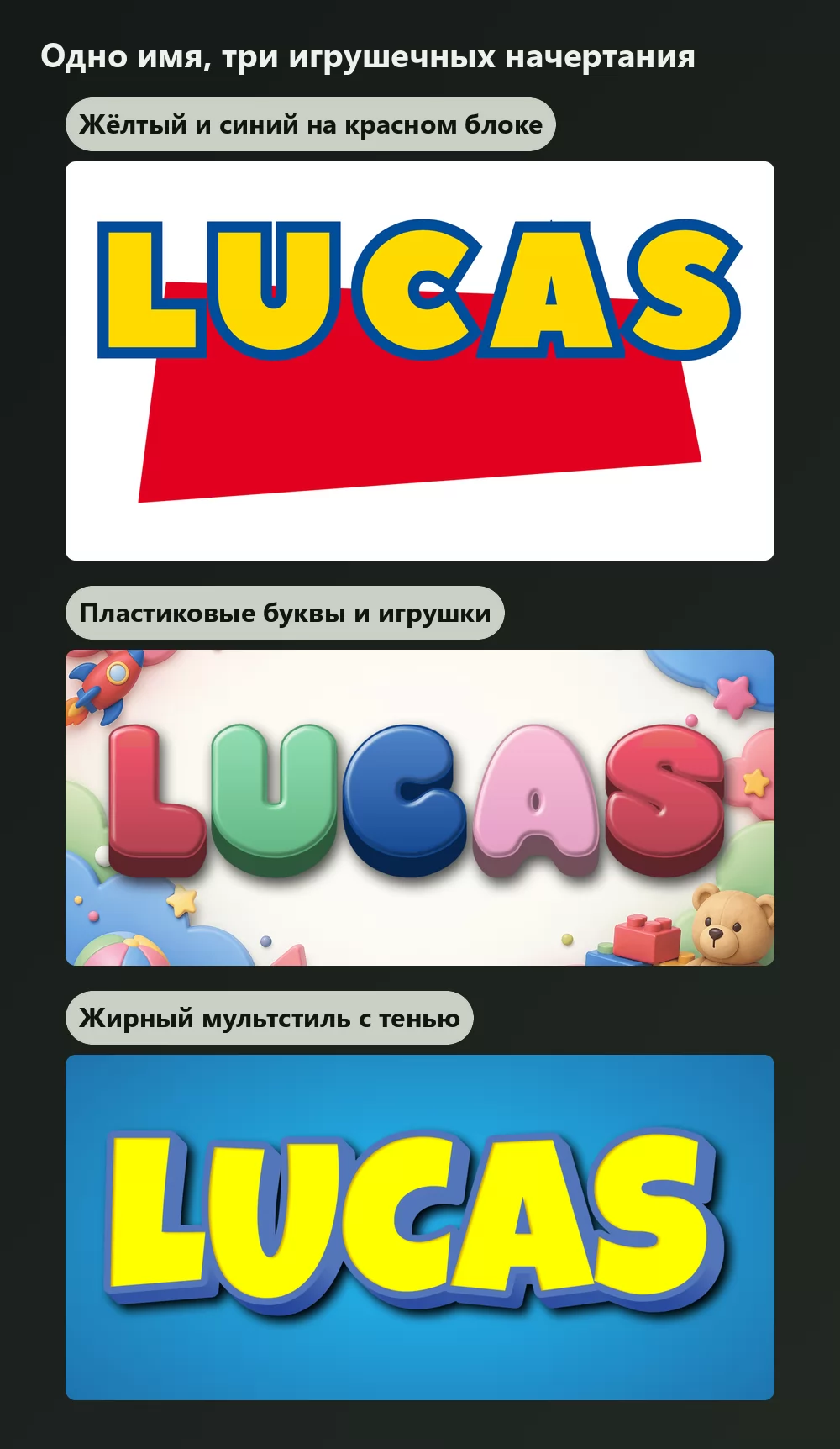
Поищите шрифт «Истории игрушек», и вы получите длинный список загрузок, каждая из которых выглядит слегка не так. Это не невезение. Логотип «Истории игрушек» это не одна гарнитура, а две, и большинство страниц с загрузками отдаёт вам лишь приблизительную версию одной из них.
Хорошая новость в том, что вторую половину вы, возможно, уже держите на компьютере, с законной лицензией, сами того не зная.
Это руководство разделяет их, точно говорит, что можно делать с каждой (именно здесь большинство страниц выражается туманно), перечисляет четыре элемента, из-за которых надпись читается как «Toy Story», и показывает, как получить результат, ничего не устанавливая. Все изображения ниже сделаны в генераторе шрифта Toy Story от TextStudio.
Логотип это две гарнитуры, а не одна
Слово «TOY» это те самые толстые округлые буквы, которые все себе представляют. Их нарисовали для фильма. Как шрифт они никогда не выпускались, поэтому легального файла с ними нет нигде.
Слово «STORY» это маленькое слово внутри красной фигуры, и это настоящая коммерческая гарнитура: Gill Sans Ultra Bold. Эрик Гилл нарисовал семейство Gill Sans для Monotype в 1928 году; начертание Ultra Bold самое жирное, именно оно здесь и использовано.
Это разделение и объясняет разочарование от загрузок. Файл с названием «шрифт Toy Story» даёт вам двойника нарисованной вручную половины и ничего для второй, тогда как композицию держит именно сочетание обеих.
Возможно, половина у вас уже есть?
Вполне вероятно, и на эту проверку стоит потратить две минуты, прежде чем что-то скачивать.
На Mac: да. Gill Sans UltraBold поставляется вместе с macOS, и так уже много версий подряд, вплоть до текущей. Откройте «Шрифты» и наберите «Gill», прежде чем искать где-то ещё.
С установленным Microsoft Office: да. Семейство Gill Sans MT, которое кладёт Office, включает Gill Sans Ultra Bold и Gill Sans Ultra Bold Condensed, и под Windows, и на Mac.
На голой Windows без Office: нет. Gill Sans не является системным шрифтом Windows. Если заглянуть в папку шрифтов машины с Windows, где Office не установлен, не найдётся ни одной Gill Sans, ни в одном начертании. Если это ваш случай, эта половина платный шрифт Monotype, а не то, что берут на сайтах с загрузками.
Честный ответ на вопрос «бесплатен ли шрифт Toy Story» звучит так: половина уже стоит у вас, если вы на Mac или у вас есть Office, а вторая половина никогда шрифтом и не была.
Половину «TOY» не выпускали, так какие есть двойники?
Раз за разом всплывают названия Agent Red и Agent Orange от Pizzadude, а также SF Slapstick Comic. По духу они близки: жирные, округлые, слегка шатающиеся прописные.
Практическая граница: свободно оформляйте что угодно для себя и близких и останавливайтесь перед всем, что продаёте или чем продвигаете бизнес.
Что на самом деле создаёт узнаваемость Toy Story
Это та часть, которую страницы с загрузками пропускают, и она весит больше, чем точная гарнитура. Работу делают четыре вещи:
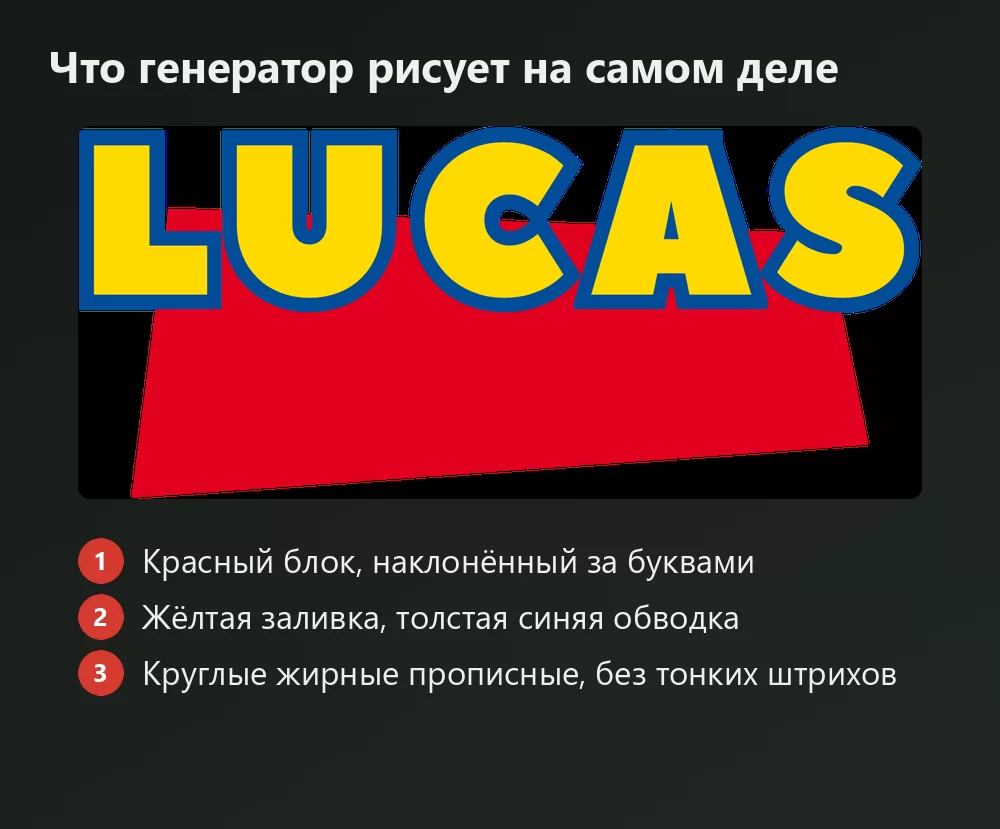
- Красный четырёхугольник, наклонённый в одну сторону, лежащий за заголовком пятном цвета, а не аккуратным прямоугольником.
- Заголовок, наклонённый в другую сторону, так что два угла противопоставлены. Этот встречный наклон и несёт почти всю энергию композиции.
- Жёлтая заливка с плотной синей обводкой, пара основных цветов, на которой держится вся франшиза.
- Слегка перекошенные буквы, каждая под своим небольшим углом, будто расставленные ребёнком, а не набранные.
Попадите в эти четыре пункта, и стиль сработает даже с приблизительной гарнитурой. Возьмите точную гарнитуру, но пропустите встречный наклон, и о Toy Story не напомнит ничего.
Честное замечание о картинке выше: генератор даёт вам наклонённый красный блок, жёлтую заливку и синюю обводку, а текст ставит ровно. Если нужен встречный наклон и углы для каждой буквы, как в оригинале, выгрузите прозрачный PNG и поверните его сами на пару градусов. Этот последний шаг занимает пять секунд и отделяет «похоже» от «точно».
Есть ли у меня Gill Sans? На Mac да. С установленным Microsoft Office да. На Windows без Office нет.
Какие цвета в логотипе Toy Story? Жёлтые буквы с синей обводкой на красном блоке. Яркие основные цвета повсюду, и это во многом объясняет, почему стиль узнаётся с первого взгляда.